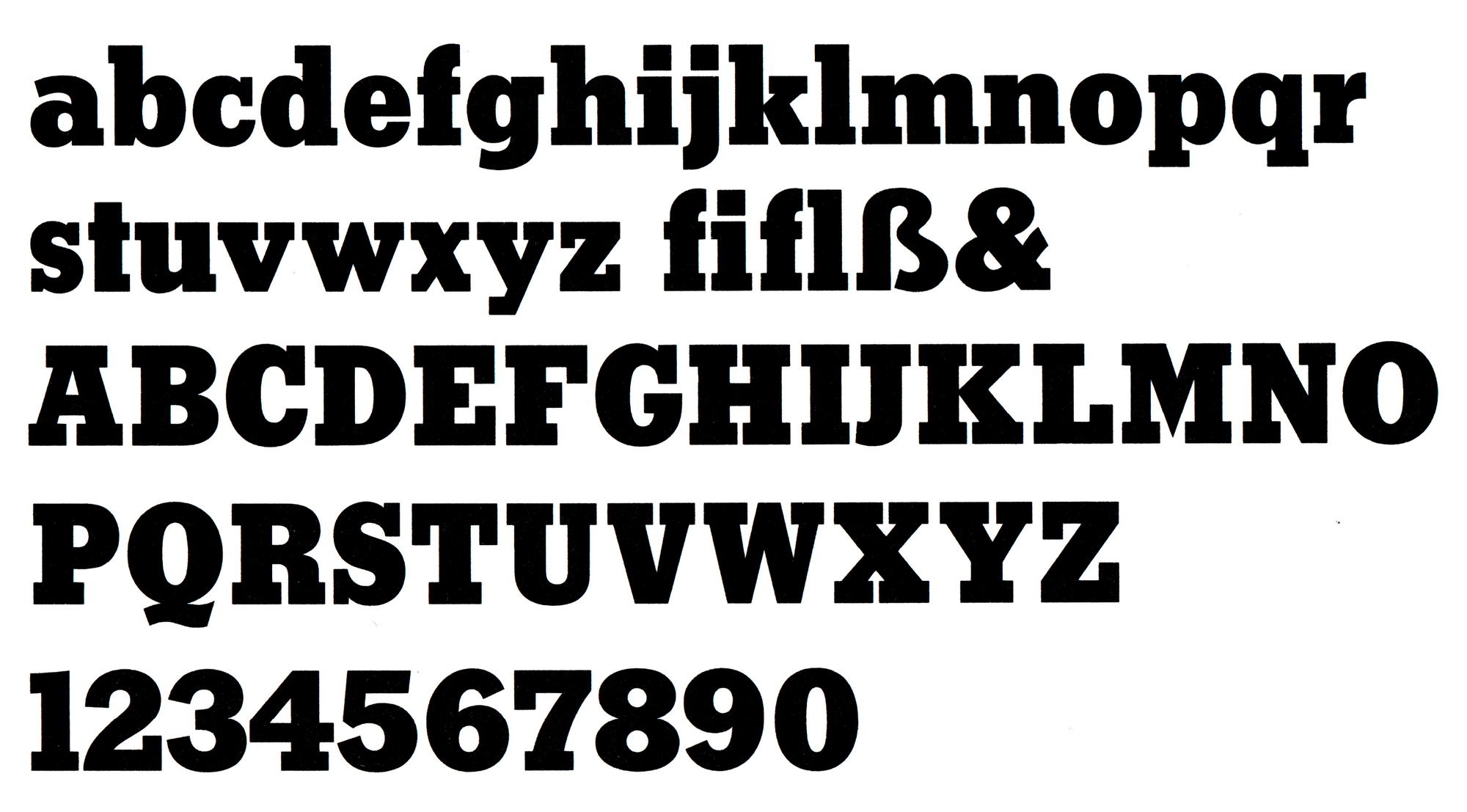
Font-Wiki: Stymie
Die Stymie von Morris Fuller Benton erschien 1931 bei American Type Founders. Später wurden von Sol Hess weitere Schnitte für Lanston Monotype hinzugefügt. Die Schrift geht auf die gleichen Schnitte wie die Rockwell zurück und ähnelt ihr daher auch.
Digitalisierungen gibt es von URW++, Linotype, Bitstream, Elsner+Flake sowie von Scangraphic.